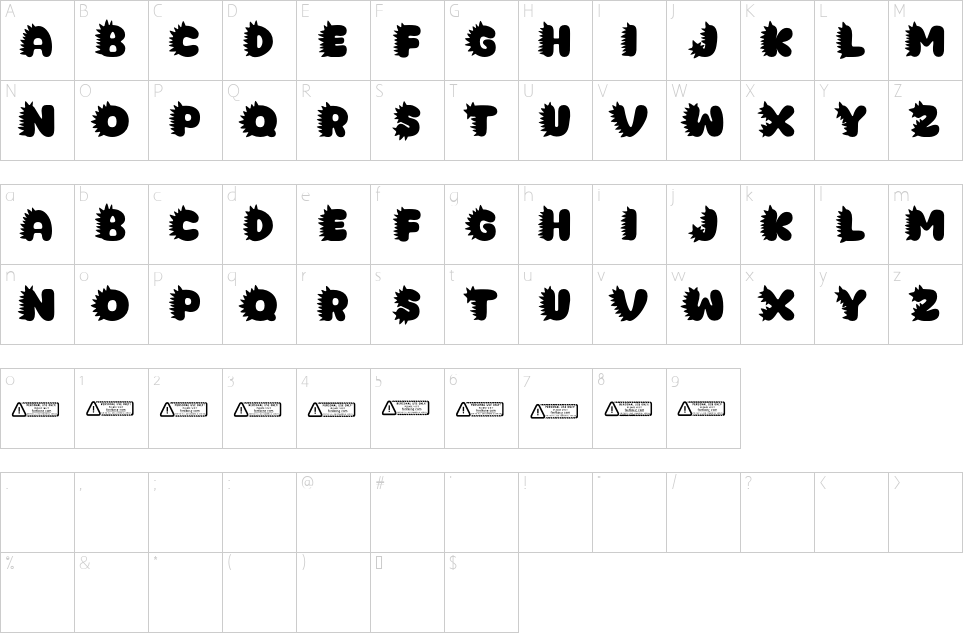
A Dino Alphabet New é uma fonte criada com a intenção de inspirar crianças a explorarem os mistérios do universo dos dinossauros. Desenvolvida por Font Kong, esta fonte é não apenas um recurso útil para quem procura personalizar o layout de suas páginas e documentos, mas também um convite ao fascínio pela história geológica e ao entusiasmo pelo aprendizado. A beleza única da Dino Alphabet New reside no seu design inspirado em dinossauros, que oferece uma paleta de formas geométricas e texturas exuberantes. Ela é perfeita para quem busca algo único e divertido para seus projetos digitais. Com 26 letras capazes de imitar o som dos dinossauros que habitaram nossas terras há milhões de anos, a Dino Alphabet New não apenas oferece uma fonte visualmente atraente, mas também um lembrete da interconexão entre os tempos modernos e passados. Esta fonte é especialmente adequada para uso em materiais educacionais infantis, desde livros de texto até aplicativos digitais. Ela também se destaca como uma escolha versátil para designers gráficos que procuram dar um toque único às suas criações. A Dino Alphabet New é perfeita para qualquer projeto que busque misturar criatividade com conhecimento, tornando-a não apenas uma fonte de código aberto, mas também um pedaço do passado vivendo em nossas telas digitais.